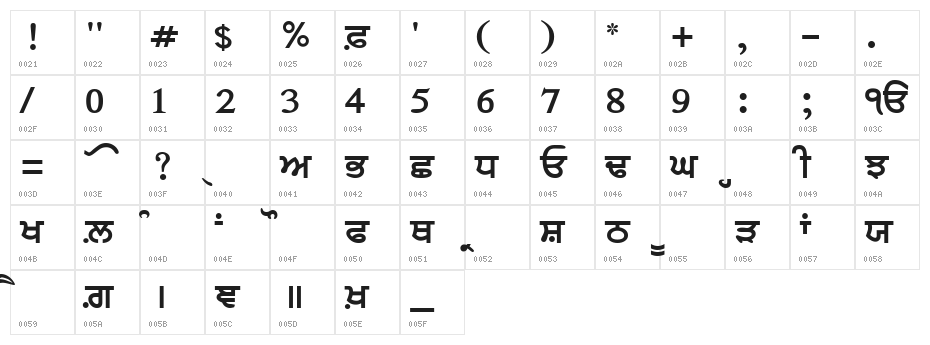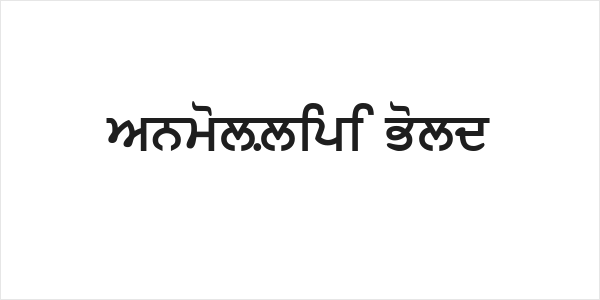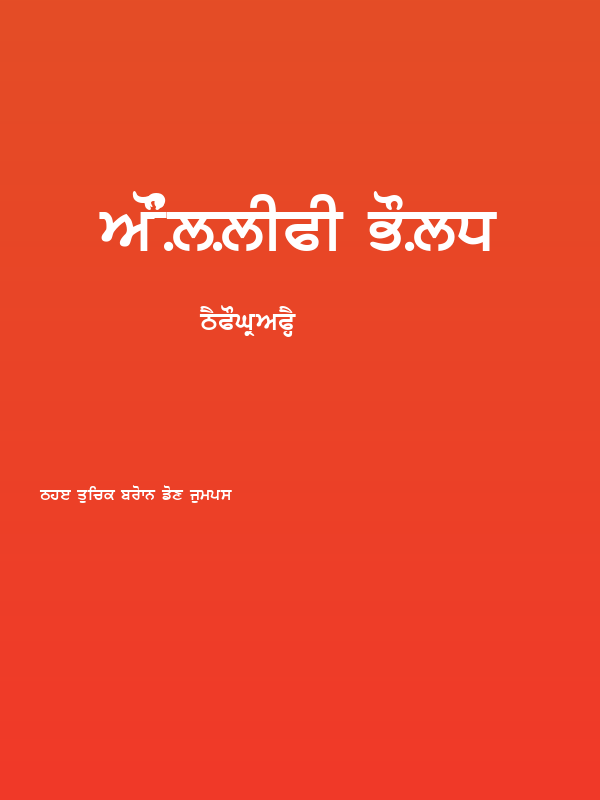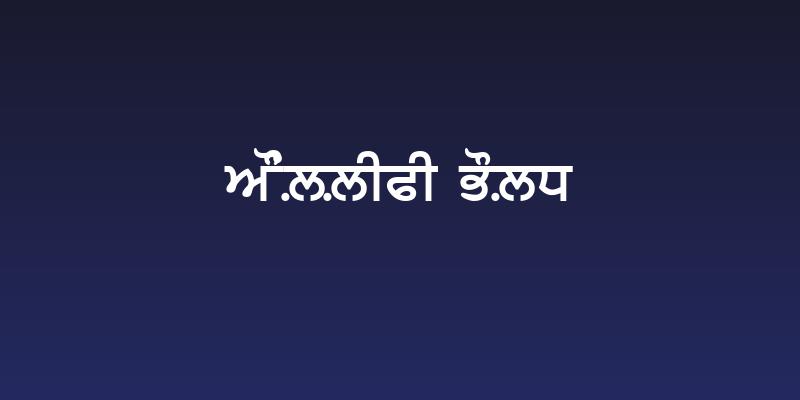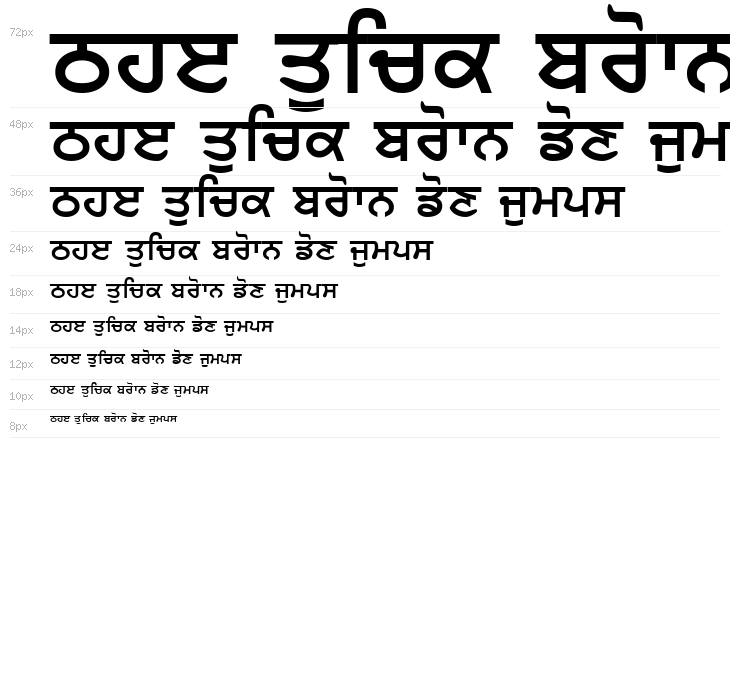
AnmolLipi Bold Font
| 使用场景 | Headlines, Logos, Signage |
| 推荐项目 | This font is perfect for projects that require a bold and authoritative presence, such as posters, banners, and signage. It can also be used in branding materials where a strong visual impact is desired. |